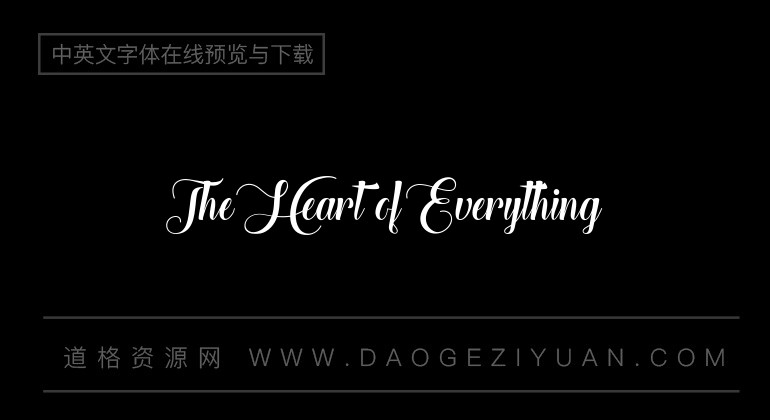
The Heart of Everything 字体是一种艺术风格的字体,由英国的字体设计师DaFont设计。这种字体采用了不规则的线条和装饰性的元素,使得它看起来非常独特和美观。 The Heart of Everything 字体适用于各种场合,尤其适合用于艺术设计、情书、海报、卡片等需要突显情感和个性的场合。它的设计灵感来源于19世纪的文艺复兴时期,给人一种浪漫和古典的感觉。 这种字体还具有多种变体,包括粗体、斜体、粗斜体等,能够满足不同设计需求。总的来说,The Heart of Everything 字体是一种非常有特色的艺术字体,适用于各种设计场合,让设计作品更加生动有趣。内容介绍
The Heart of Everything是一款非常不错的手写艺术字体,具有很好的视觉感,适合于文化类的宣传设计、商业类品牌的广告和产品包装设计以及个性化文字排版等较多场景。